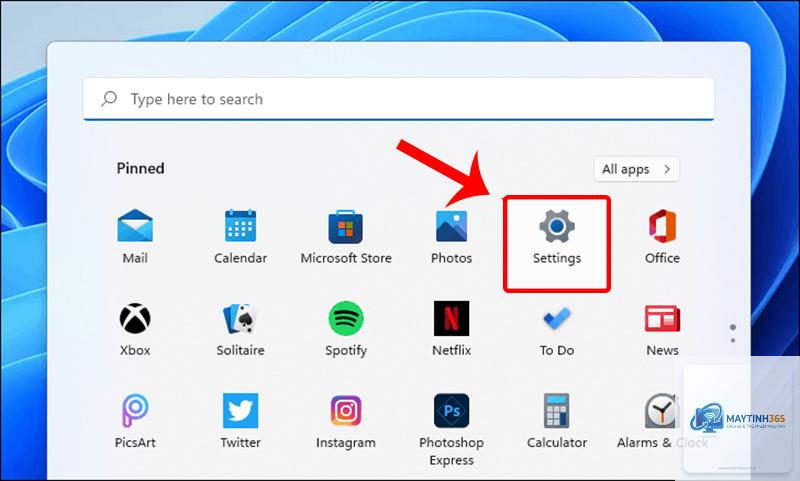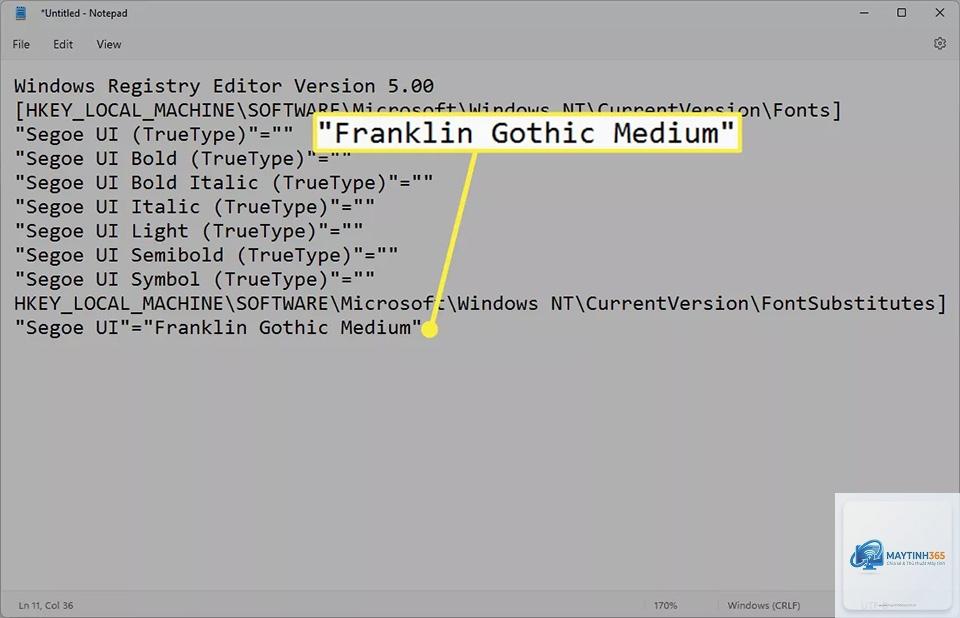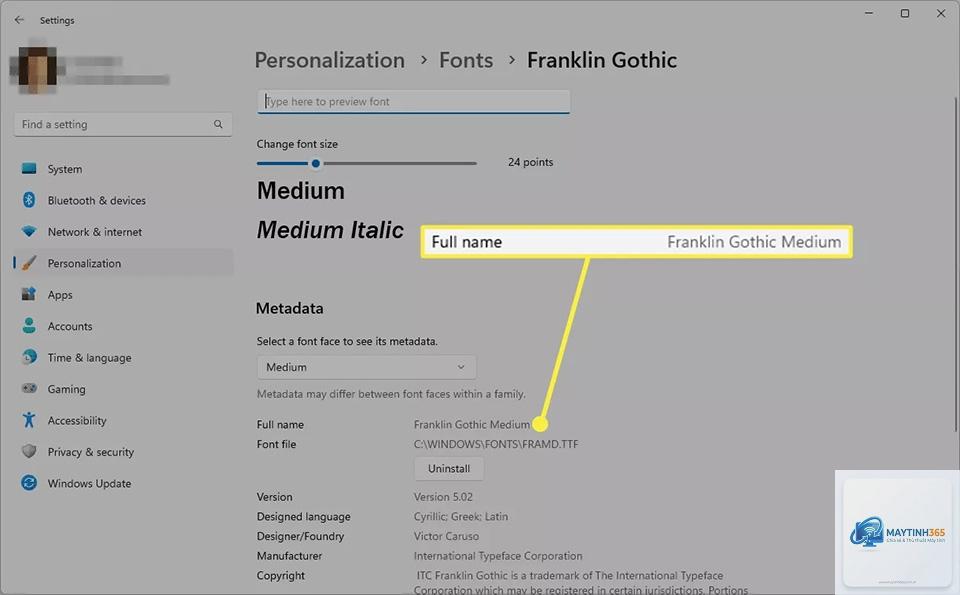
Cách thay đổi font chữ Windows 11: Hướng dẫn chi tiết từ A đến Z cho người mới bắt đầu
Việc tùy chỉnh giao diện máy tính luôn là nhu cầu của nhiều người dùng, và thay đổi font chữ là một trong những cách hiệu quả nhất để làm mới trải nghiệm. Nếu bạn đang tìm kiếm cách thay đổi font chữ Windows 11 một cách an toàn và hiệu quả, bài viết này sẽ cung cấp cho bạn mọi thông tin cần thiết. Từ các phương pháp thủ công cho đến sử dụng phần mềm chuyên dụng, tất cả đều được trình bày chi tiết, giúp bạn dễ dàng thực hiện ngay cả khi không có nhiều kinh nghiệm về máy tính.
Tại sao cần thay đổi font chữ trên Windows 11?
Windows 11 mặc định sử dụng font chữ Segoe UI Variable, một kiểu chữ hiện đại và dễ đọc. Tuy nhiên, không phải ai cũng cảm thấy hài lòng với lựa chọn này. Việc thay đổi font chữ mang lại nhiều lợi ích thiết thực.
Lợi ích của việc thay đổi font chữ
• Cá nhân hóa giao diện: Mỗi người có một gu thẩm mỹ riêng. Việc thay đổi font chữ giúp chiếc máy tính của bạn trở nên độc đáo và thể hiện cá tính.
• Cải thiện khả năng đọc: Một số font chữ được thiết kế tối ưu cho việc đọc văn bản dài, giúp giảm mỏi mắt khi làm việc nhiều giờ liền.
• Hỗ trợ người khiếm thị: Những font chữ có kích thước lớn, rõ nét hoặc chuyên dụng cho người khuyết tật thị giác có thể giúp họ tương tác với máy tính dễ dàng hơn.
• Phù hợp với nhu cầu công việc: Các nhà thiết kế, lập trình viên hoặc người làm nội dung thường cần những font chữ chuyên biệt để phục vụ công việc.
Hạn chế cần lưu ý
• Rủi ro hệ thống: Thay đổi font chữ hệ thống không đúng cách có thể gây lỗi hiển thị, thậm chí khiến một số ứng dụng không hoạt động.
• Không được hỗ trợ chính thức: Microsoft không cung cấp tùy chọn thay đổi font chữ toàn hệ thống trong Windows 11. Bạn phải can thiệp vào Registry hoặc sử dụng công cụ bên thứ ba.
• Một số font không tương thích: Không phải font chữ nào cũng hoạt động tốt trên giao diện Windows. Một số font có thể bị vỡ chữ hoặc hiển thị không đúng kích thước.
Các phương pháp thay đổi font chữ Windows 11
Có ba cách chính để thực hiện cách thay đổi font chữ Windows 11, mỗi cách đều có ưu và nhược điểm riêng.
Có hai cách để khôi phục font chữ mặc định. Cách thứ nhất là sử dụng file.reg đã sao lưu trước đó. Cách thứ hai là vào Settings -> Personalization -> Fonts, tìm đến mục “Restore default font settings” (nếu có) hoặc sử dụng công cụ Winaero Tweaker để đặt lại font về Segoe UI.
Có thể thay đổi font chữ cho từng ứng dụng riêng lẻ không?
Có, một số ứng dụng cho phép bạn thay đổi font chữ trong cài đặt riêng của chúng. Ví dụ, trình duyệt web, Microsoft Office, hoặc các phần mềm chỉnh sửa ảnh đều có tùy chọn này. Tuy nhiên, điều này không ảnh hưởng đến font chữ toàn hệ thống.
Thay đổi font chữ có ảnh hưởng đến hiệu suất máy tính không?
Thông thường, việc thay đổi font chữ không ảnh hưởng đáng kể đến hiệu suất. Tuy nhiên, nếu bạn sử dụng các font chữ có dung lượng lớn hoặc thiết kế phức tạp, máy tính có thể mất thêm một chút thời gian để render chữ, đặc biệt trên các cấu hình thấp.
Tại sao sau khi thay đổi font, một số chữ bị vỡ hoặc hiển thị dưới dạng ô vuông?
Điều này xảy ra khi font chữ bạn chọn không hỗ trợ bảng mã Unicode cho ngôn ngữ bạn đang sử dụng. Hãy chọn các font chữ hỗ trợ đầy đủ Unicode hoặc cài đặt thêm gói ngôn ngữ tương ứng.
Kết luận
Cách thay đổi font chữ Windows 11 không quá phức tạp nhưng đòi hỏi sự cẩn trọng và kiến thức cơ bản về hệ thống. Dù bạn chọn phương pháp thủ công qua Registry, sử dụng phần mềm bên thứ ba hay file.reg, điều quan trọng nhất là luôn sao lưu dữ liệu và chọn font chữ tương thích. Một giao diện với font chữ yêu thích không chỉ giúp bạn làm việc thoải mái hơn mà còn thể hiện phong cách cá nhân. Hãy bắt đầu với những bước đơn giản nhất và dần dần khám phá thêm nhiều tùy chỉnh thú vị khác trên Windows 11.